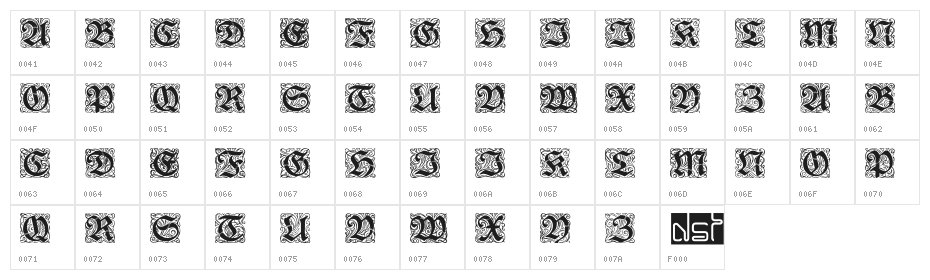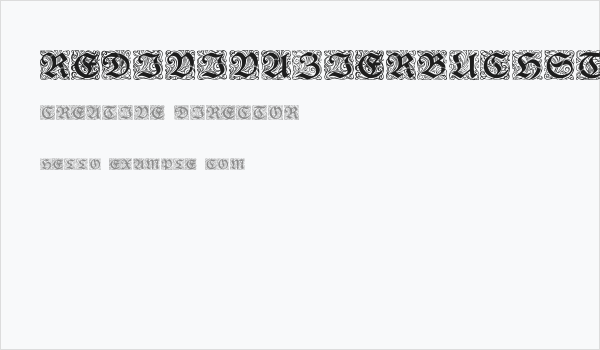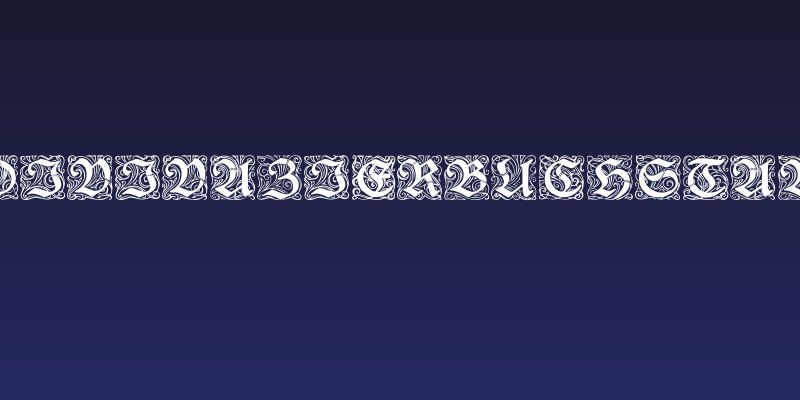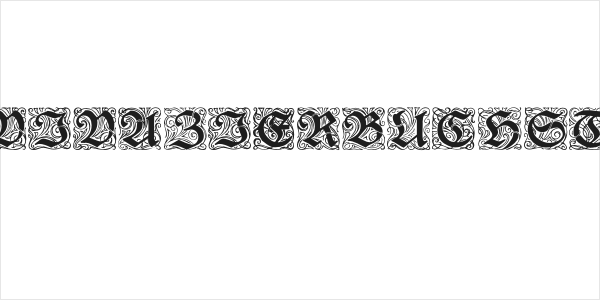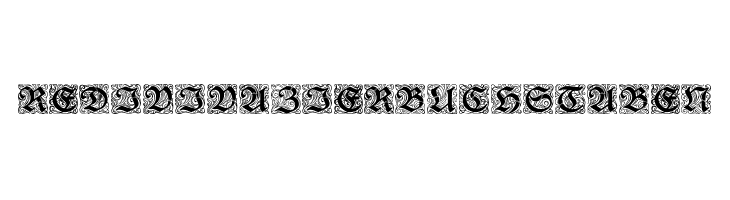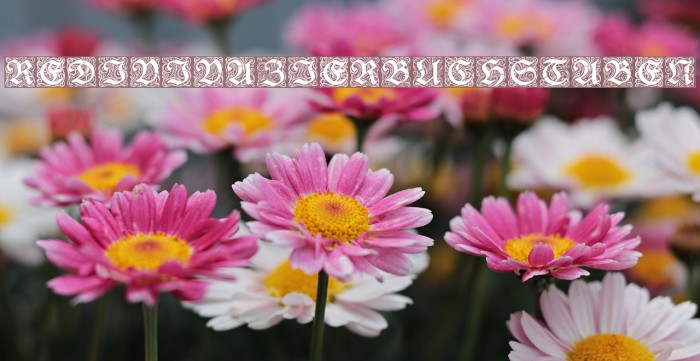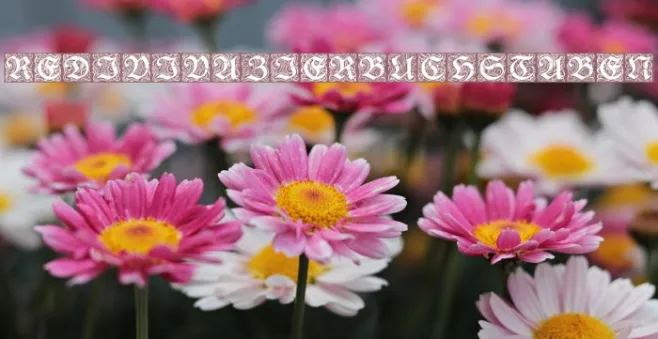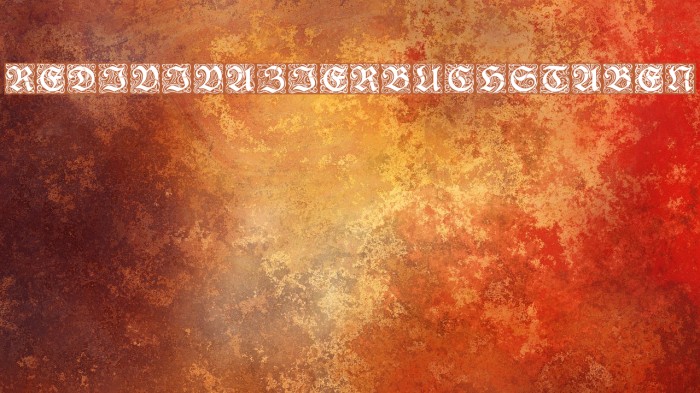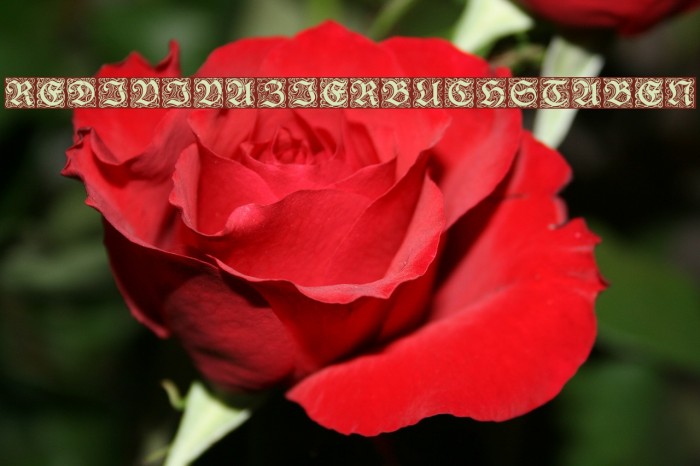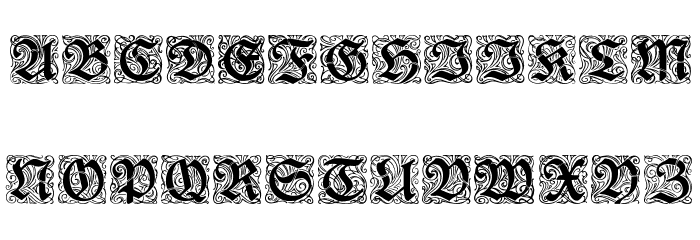
RedivivaZierbuchstaben Font
| Projets proposés | Ideal for use in invitations, certificates, book covers, and any project requiring a historical or luxurious touch. |